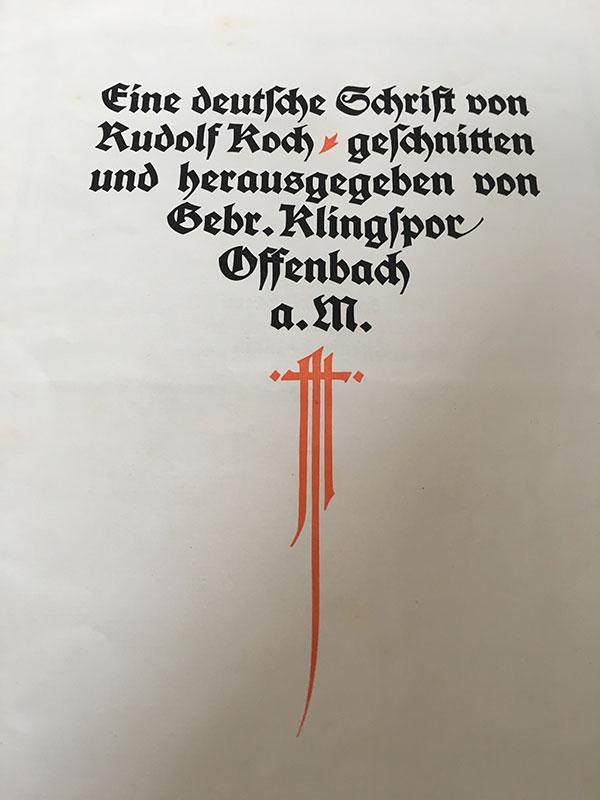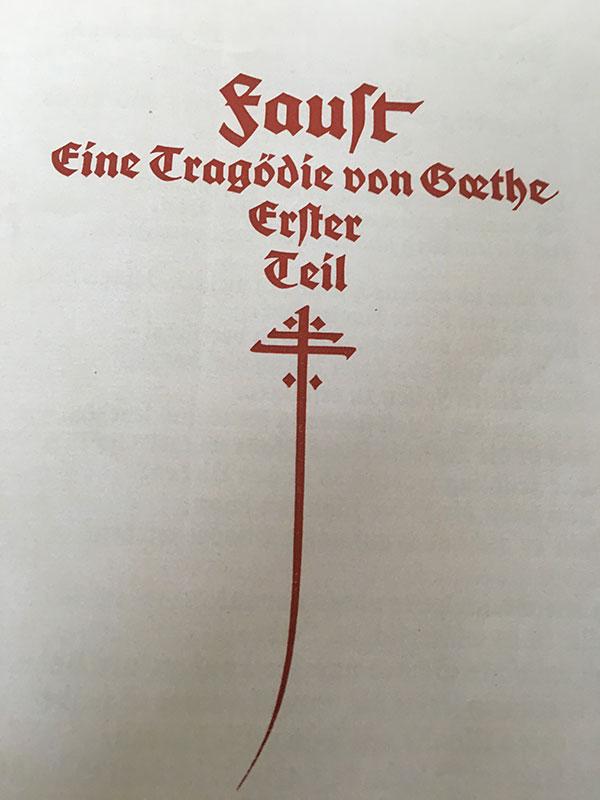
Schmuckbuchstabe oder Ornament?
Diese zwei »Lettern« hier habe ich in einer Schublade mit Schmuckbuchstaben (Bleisatz) verschiedener Größe und Gattungen gefunden.
Welchen Buchstaben stellen sie dar? Oder handelt es sich um ein Symbol?
Das sind doch wahrscheinlich auf einen Holzklotz aufgenagelte Galvanos? Buchstaben kann ich darin nicht erkennen, wenn es nicht fremdsprachige sind. Ich würde eher auf Kreuze tippen.
Korrekt. Es handelt sich um aufgenagelte Galvanos.
Tatsächlich übermitteln diese Zeichen einen geistlichen Eindruck.